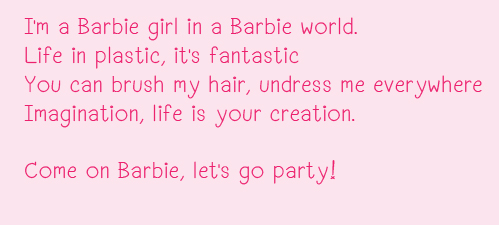
น้องใหม่ รบกวนติ-ชมด้วยค่า
คราวนี้ก็อยากมีเป็นของตัวเองบ้างสิ ,, แน่นอนว่าต้องเป็นฟอนต์ลายมือ (มาตรฐานเด็กใหม่ ,, แหะ ๆ)
ถึงมันจะดูธรรมดา ๆ (ก็ลายมือวัยรุ่นนี่นา)  ยังไงก็รบกวนช่วย ติ-ชม หรือติอย่างเดียวก็ได้ด้วยนะคะ
สวยงามครับ  :25:
ตอนนี้ ผมก็คงจะยังไม่มีอะไรติหรอกครับ  :42:
ดูลงตัวมากครับ ทั้งภาษาไทยและอังกฤษดูมันไหลลื่นไปตามลูกกะตาเลย
ดูดี  เรียบร้อย  สวยครับ   :12:
ปล.  แอบชอบ ก.ไก่  กวนดีครับ   :42:
ชอบ ก กับ ห เหมือนกันครับ
ดูแล้วเตะตาเขียวเลย
โดยรวมอ่านง่าย โปร่งตา แจ๋วครับ:12:
ขอคำนี้ครับ
ปีใหม่นี้นู๋โตแล้วตามพี่ไปโรงเรียน
โฮ่ เจ๋ง ทำนานไหมนี่เเบบนี้ :45:
เพิ่งเข้ามาดู  กำลังจะมาบอกว่าชอบ ก.ไก่เหมือนกันค่ะ
ฟอนต์นี้ใช้เวลาทำประมาณ 3-4 วันคะ  :07: เป็นฟอนต์แรกในชีวิต + ใช้โปรแกรมไม่ค่อยเป็น
สวยครับ มีอย่างเดียวคือ น หนู กับสระ อี หรือ จัตวา (อาจรวมถึงวรรณยุกต์และสระตัวอื่นๆ ด้วย) มันไม่ตรงกันกับหาง น หนู น่ะครับ
วิธีแก้ แก้ด้วย kerning หรือไม่ก็สร้าง Glyph สระชุดกระเถิบซ้ายเล็กๆ แล้วใช้ opentype เข้าช่วยครับ